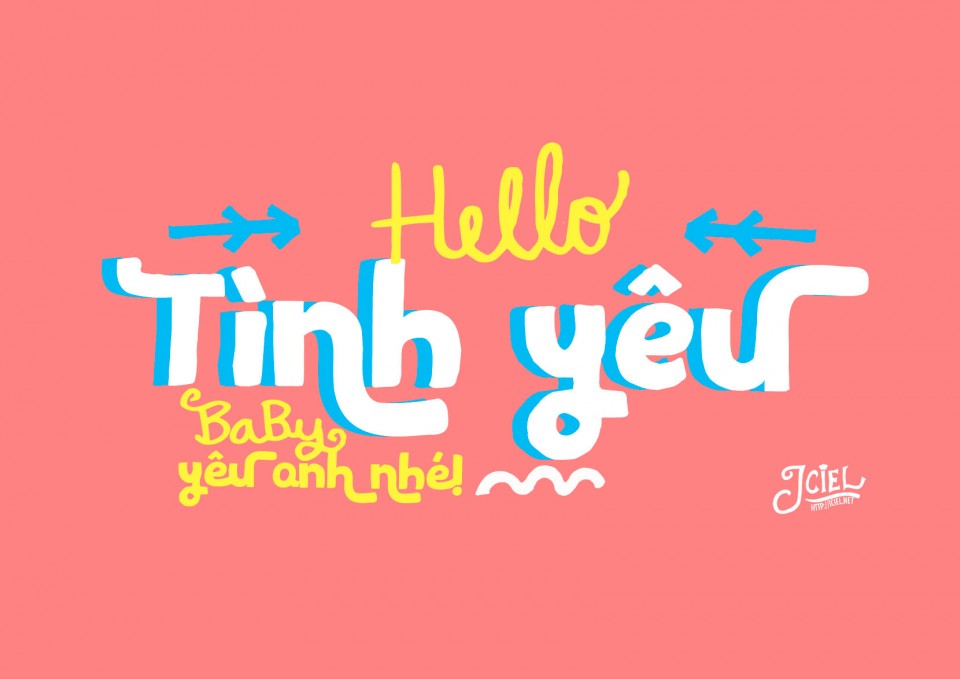
Font việt hóa iCiel Pequena Pro: Lựa chọn hoàn hảo cho thiết kế giáo dục
Giới thiệu về Font việt hóa iCiel Pequena Pro
Trong thế giới đồ họa hiện đại, việc tìm kiếm một bộ Font Miễn Phí chất lượng luôn là ưu tiên hàng đầu của các nhà thiết kế. Font việt hóa iCiel Pequena Pro nổi lên như một giải pháp lý tưởng dành cho những ai yêu thích phong cách trẻ trung và gần gũi. Đây là bộ phông chữ được tinh chỉnh kỹ lưỡng về dấu tiếng Việt, giúp các văn bản trở nên chuyên nghiệp và hài hòa hơn bao giờ hết. Với những đường nét bo tròn mềm mại, bộ font này cực kỳ phù hợp cho môi trường học tập và giảng dạy tại Việt Nam.
Đặc điểm nổi bật của bộ Font việt hóa iCiel Pequena Pro
Phong cách thiết kế sáng tạo
Font việt hóa iCiel Pequena Pro mang trong mình vẻ đẹp của sự giản đơn nhưng không kém phần tinh tế. Các ký tự được thiết kế với độ dày vừa phải, tạo cảm giác thân thiện và dễ đọc ngay cả ở kích thước nhỏ. Điểm đặc biệt của nó chính là khả năng truyền tải cảm xúc vui tươi, rất thích hợp để làm tiêu đề bài giảng, thiết kế thiệp chúc mừng hay các ấn phẩm dành cho học sinh tiểu học.
Tính ứng dụng linh hoạt trong đời sống
Không chỉ dừng lại ở mảng giáo dục, bộ phông chữ này còn phát huy tác dụng mạnh mẽ trong lĩnh vực quảng cáo và làm thương hiệu. Bạn có thể sử dụng nó để trang trí bìa sách, làm infographic hoặc thiết kế giao diện ứng dụng di động. Sự đa dạng trong các biến thể giúp người dùng dễ dàng kết hợp với nhiều phong cách khác nhau từ cổ điển đến hiện đại.
Kết luận về trải nghiệm người dùng